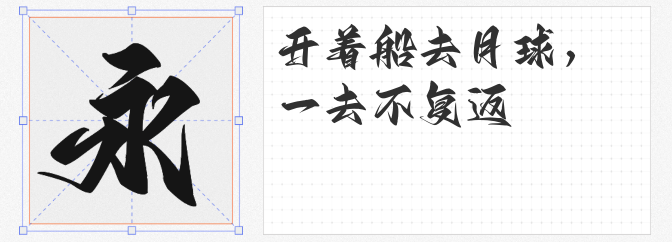
在国潮崛起的浪潮中,字体设计成为传递文化基因的关键载体。以下四款免费商用字体,既承袭传统书法精髓,又融入现代设计巧思,助力设计师轻松打造兼具文化底蕴与视觉张力的作品。
1.阿里妈妈东方大楷
以颜真卿《多宝塔碑》为蓝本,通过算法学习其笔法,再经人工精修,东方大楷完美还原了书法中的提按转折与护尾藏锋。横画如绵里藏针,竖画似铁柱擎天,中宫疏朗而外围舒展,既保留了唐楷的法度森严,又通过数字化优化提升了阅读舒适性,适用于品牌标题与文化类海报设计。
2. 阿里妈妈刀隶体
萃取爨宝子碑的方峻笔意,阿里妈妈刀隶体将隶书波磔与楷法结构熔铸一炉。三角点折如刀刻斧凿,横画两端雁尾高扬,字形欹侧险绝却气韵生动。这种"破衡求美"的设计哲学,尤其适合需要视觉冲击力的国潮包装与电竞海报,让文字成为传递态度的视觉符号。
3. Aa剑豪体
首款免费商用的剑豪体自带武林气韵,笔画如剑锋出鞘,转折处龙蛇飞动。连笔处虽显狂放,却始终遵循书法韵律,恰似侠客杯中酒,既有"十步杀一人"的凌厉,又不失"醉卧沙场君莫笑"的洒脱。适用于武侠游戏界面、音乐海报等需要传递豪迈之气的场景。
4. 龚帆免费体
这款字体如文人信札般温润,毛笔飞白与提按痕迹清晰可见。圆润的笔画与柔和的转折,恰似宣纸上晕染的墨痕,自带"见字如面"的亲切感。特别适合茶饮包装、民宿导视等需要传递温暖质感的领域,让设计既有专业度又不失人情味。